Top 10: Tipografías icónicas de bandas de rock
Descubre tipografías que usan algunas de las bandas más icónicas de la historia
Estas bandas han logrado consolidarse en la memoria del mundo no solo por su música, sino por la identidad gráfica que usaron en sus logotipos, portadas de álbumes y shows en vivo. Descubre a continuación detalles interesantes sobre las tipografías creadas a partir del concepto musical de 10 de los grupos de rock más importantes de la historia.
The Beatles
El logotipo del Cuarteto de Liverpool está basado en una fuente serif llamada Bootle, y su principal característica es, además de su simpleza, la T alargada. Fue creada por el dueño de una tienda de instrumentos musicales, Ivor Arbiter, a quien el grupo pidió que grabara el nombre de la banda en el bombo de la batería.
Pink Floyd
El diseño que fue pensado para ser el arte para el álbum The Wall, terminó convertido en una tipografía que, hasta hoy, sigue siendo replicada por miles de personas alrededor del mundo. Fue creado en 1975 por Gerald Scarge, artista visual que además estuvo a cargo de muchos de los visuales de la banda durante sus conciertos. En 1995 nació finalmente la fuente que deriva de esta idea, y se llama Floydian.
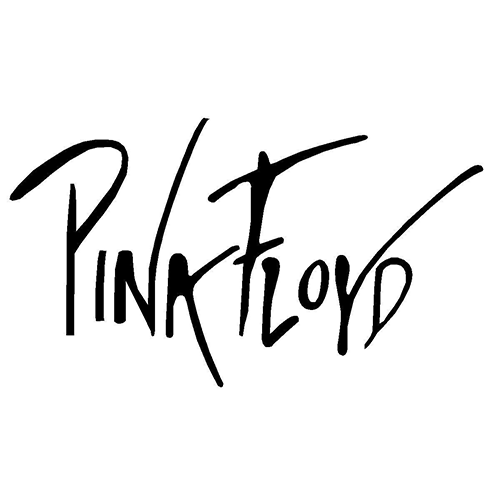
AC/DC
Basada en el lettering de estilo gótico, esta tipografía vio la luz por primera vez cuando fue plasmada en el cover del álbum Let there be rock. Tanto el logo como la fuente son atribuidos al entonces director de arte de Atlanta Records, Bob Defrin, aunque es a Ray Larabie, a quien se le adjudica el derecho sobre Squealer, la tipografía adaptada del logotipo de AC/DC.
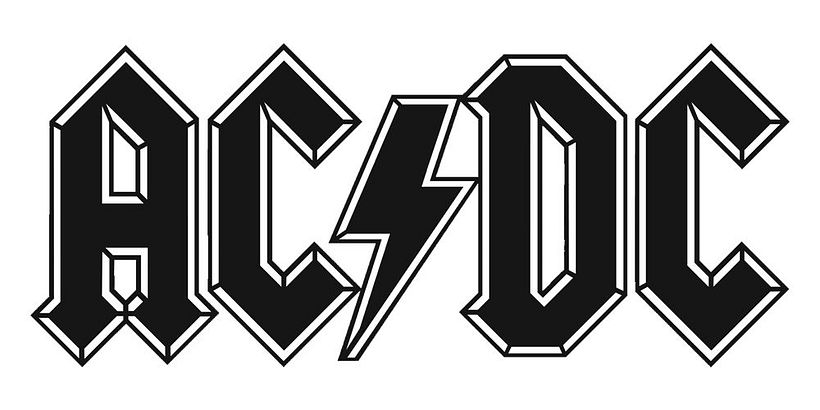
Metallica
Sin duda, una de las tipografías más reconocibles en la música. El logo de la banda fue diseñado por el guitarrista de la banda, James Hetfield, en 1983, e incluido en el álbum Kill’em All. Está basado en letras mayúsculas en estilo bold, con la variación clásica en la primera y la última letra del nombre de la banda. Posteriormente, en 1997, Ray Larabie desarrolló el alfabeto tipográfico de este diseño y nombró a esta fuente Pastor of Muppets.
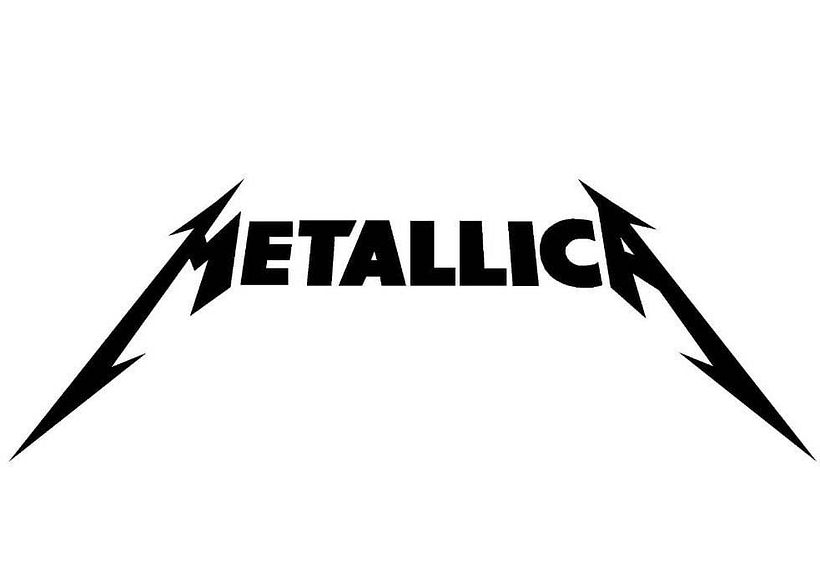
Iron Maiden
Nuevamente es Larabie el nombre detrás de la fuente surgida a partir del logotipo de esta banda, creado por el bajista de Iron Maiden, Steve Harris. Se llama Metal Lord, y está caracterizada por el manejo de formas triangulares y las icónicas modificaciones en las letras O y D.
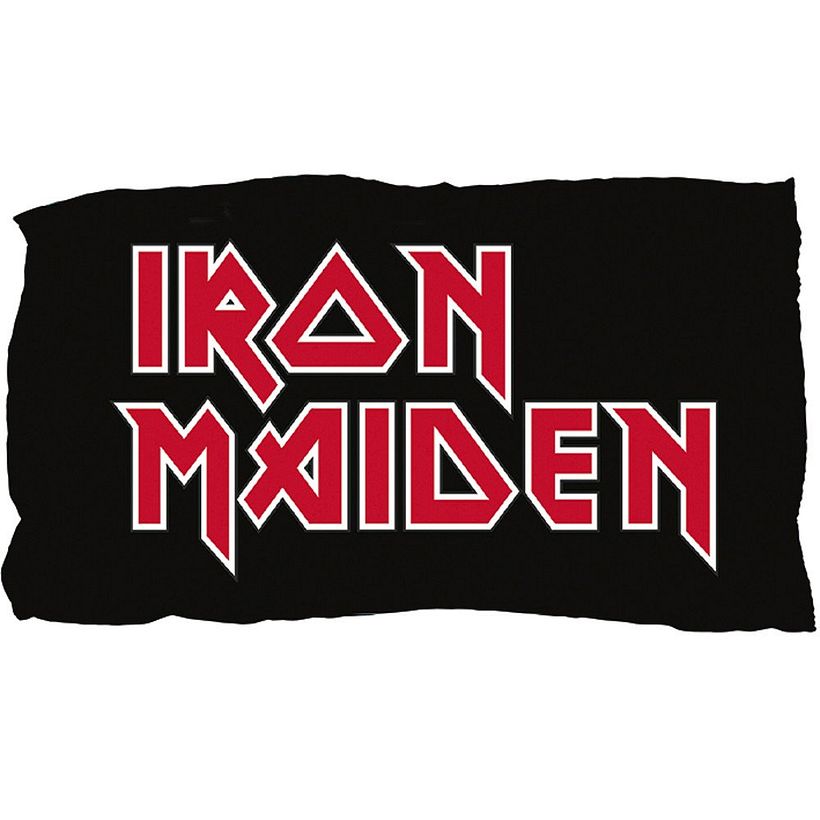
Kiss
Diseñado por Ace Frehley, el logotipo apareció por primera vez en el álbum Hotter Than Hell y, aunque originalmente la letra S tenía un estilo mucho más angular y afilado, debido a la relación gráfica con la SS (agencia secreta de inteligencia nazi —Schutzstaffel—), al diseño de las letras se le agregaron más curvas para suavizar los ángulos.
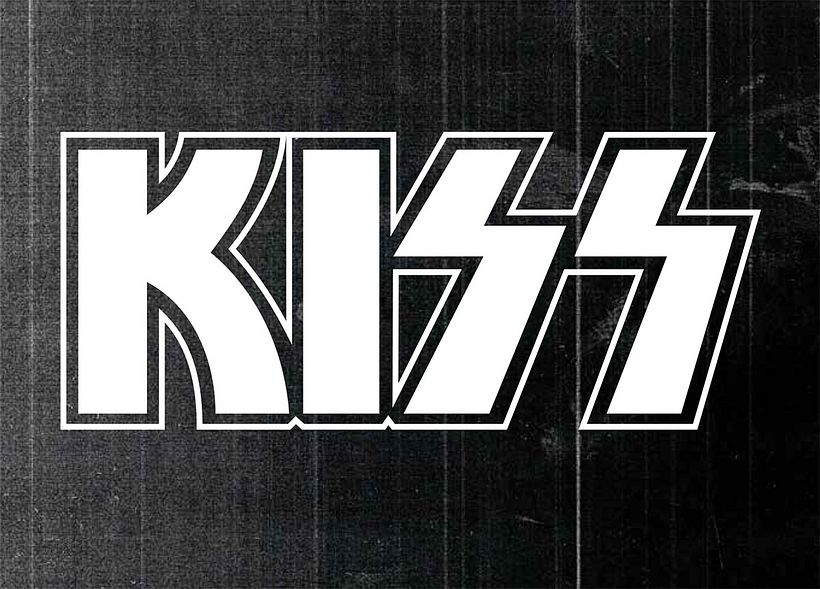
Nirvana
La fuente usada en el logo de esta banda de grunge es una versión condensada de Poster Bodoni, diseñada originalmente en 1798 por el impresor y tipógrafo Giambattista Bodoni, a quien se le atribuyen varias fuentes usadas aún en la actualidad.
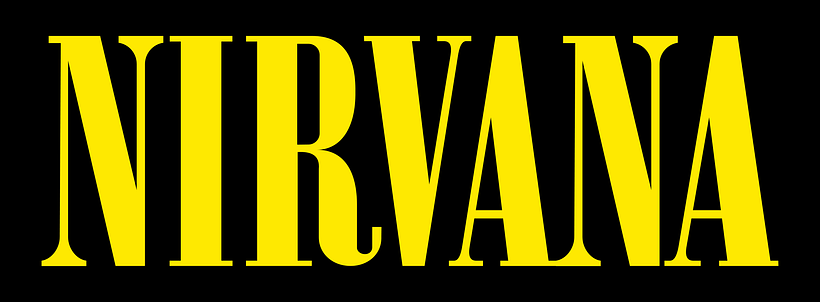
Red Hot Chili Peppers
Uno de los logotipos estrella del rock está basado en una de las fuentes más populares: Arial Black. Sin embargo, la banda llegó a usar una variación de esta tipografía en el logo plasmado en la cubierta del álbum Mother’s Milk, en el que usaron Franklin Gothic.
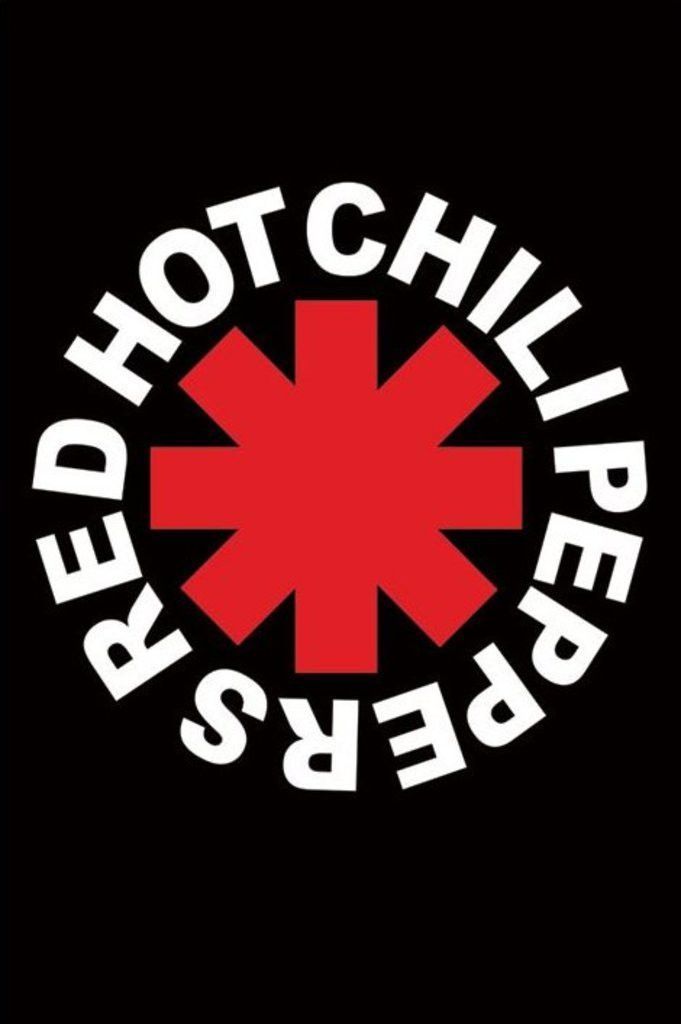
Muse
El logotipo de esta banda fue diseñado a partir de la fuente Frutiger 65 Bold que, a su vez, fue creada por Adrian Frutiger en 1976, como parte de una familia completa de estilos caracterizada por su simpleza y su legibilidad.
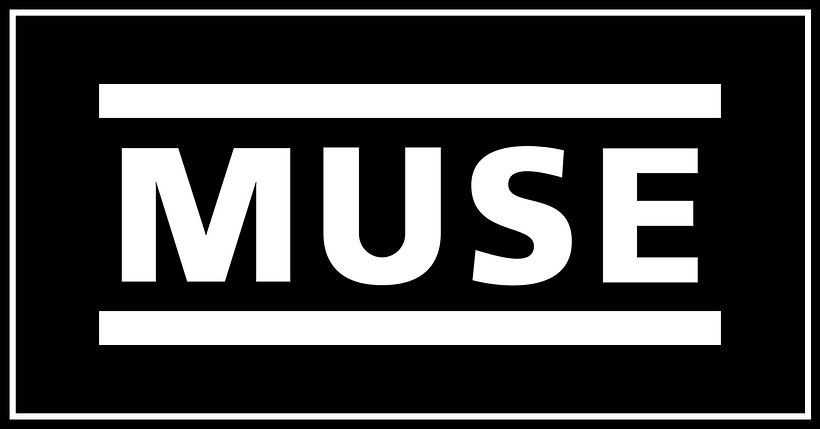
Linkin Park
El logotipo de esta banda fue rediseñado varias veces. El ícono está compuesto por las letras L y P invertidas, presentadas en una fuente sans serif condensada. En cuanto a la fuente usada para el nombre de la banda, replica la esencia de la imagen pero en una versión más condensada y con un detalle de prolongación angular en las letras N, A y R.